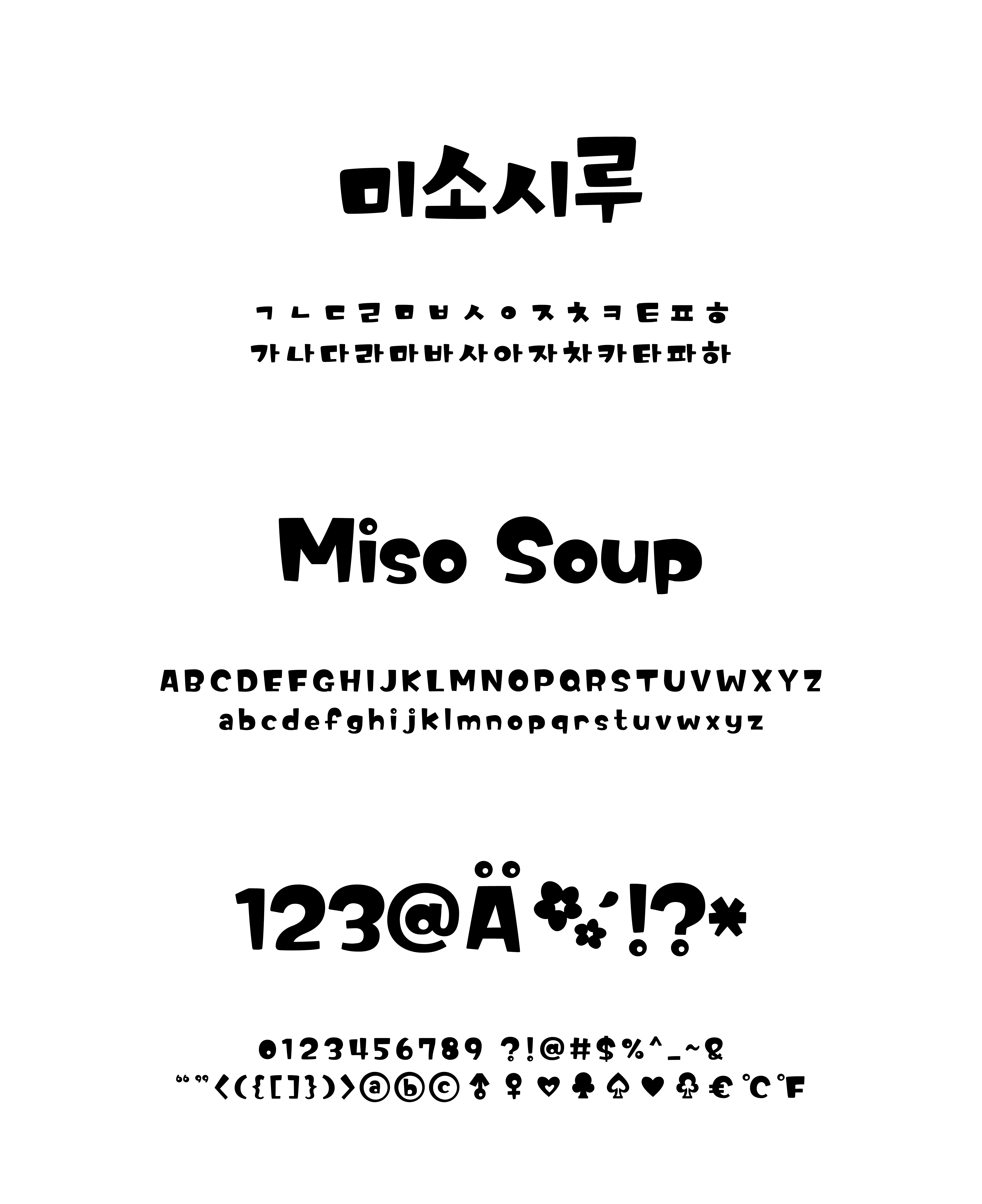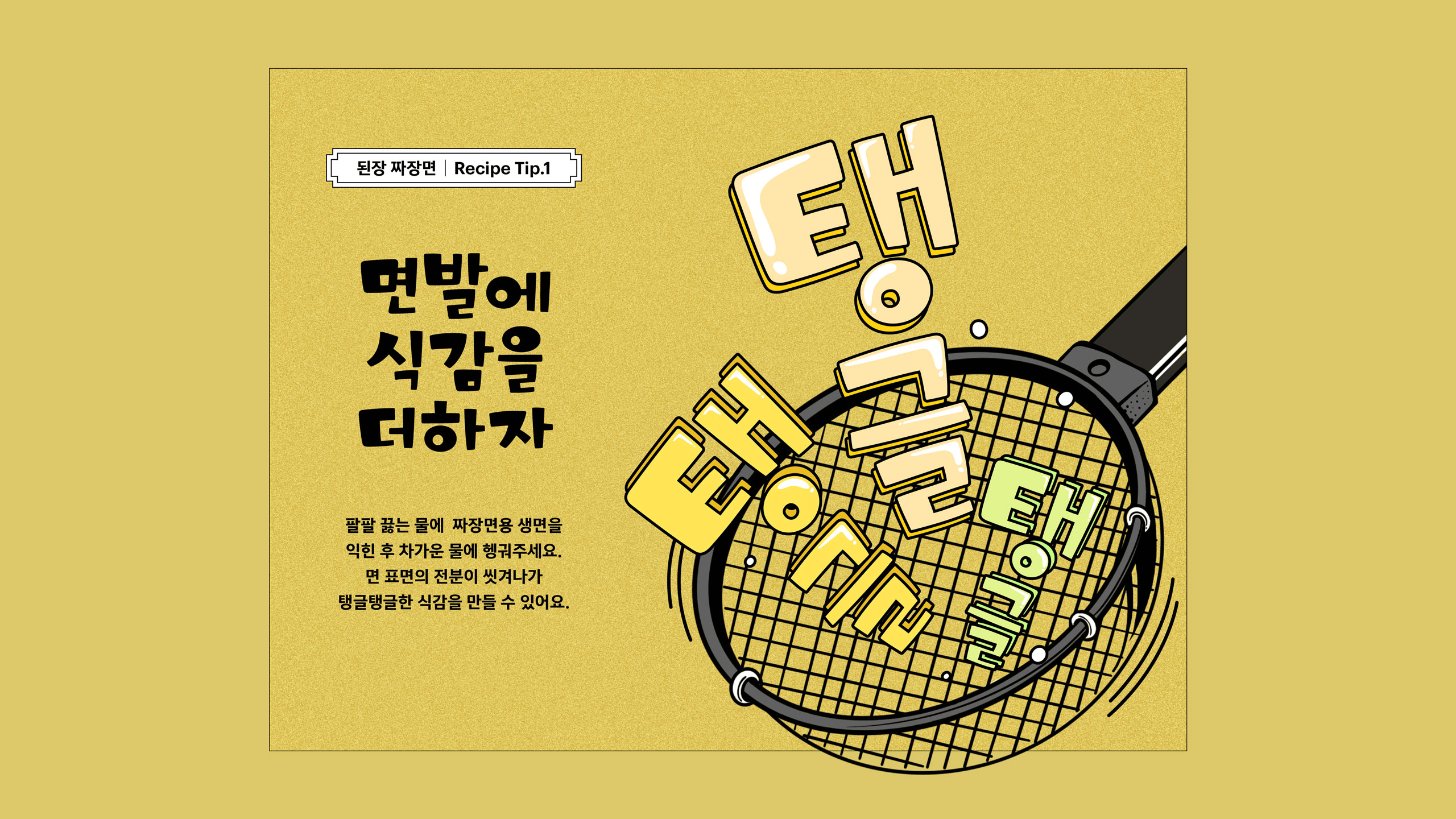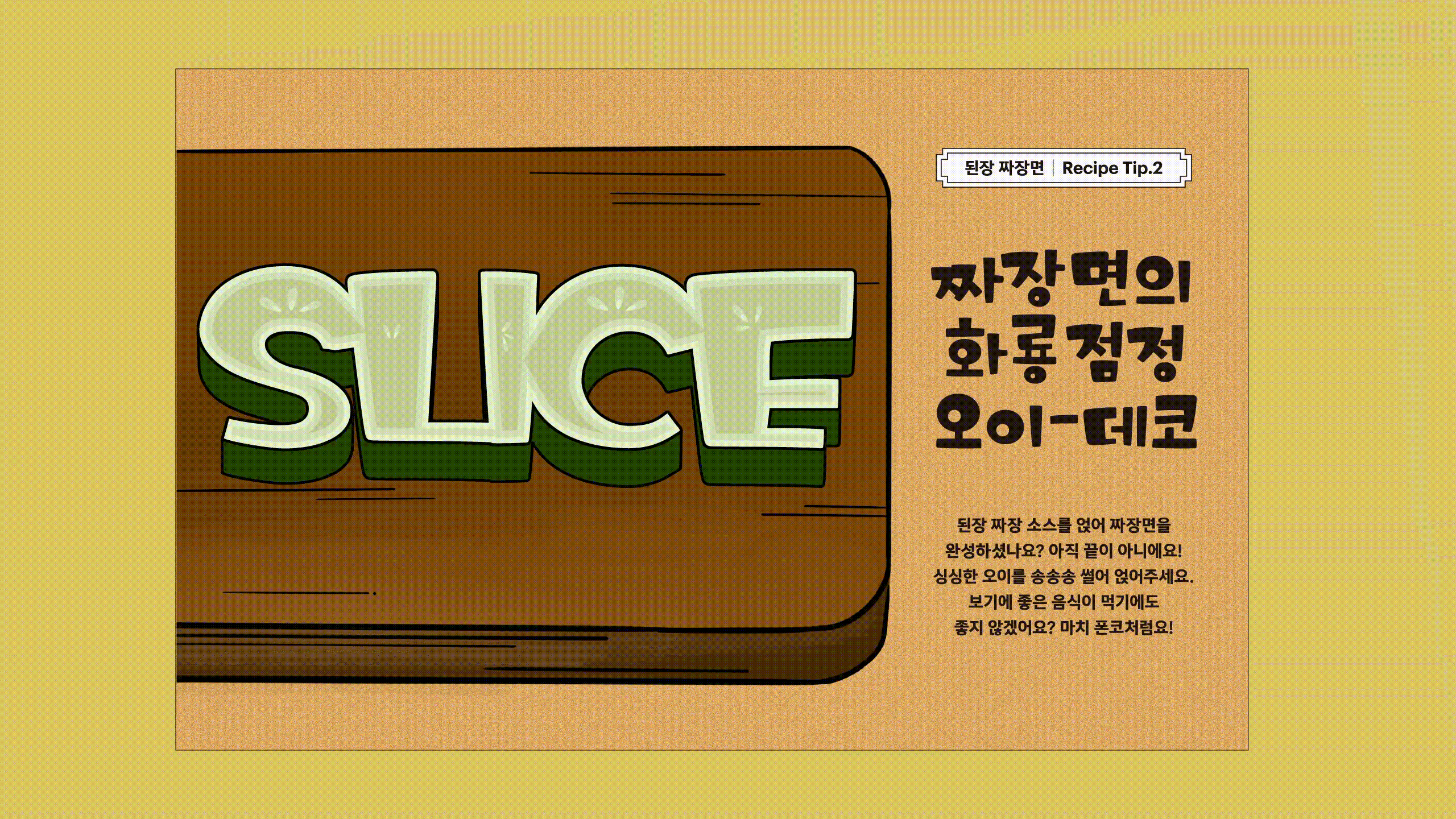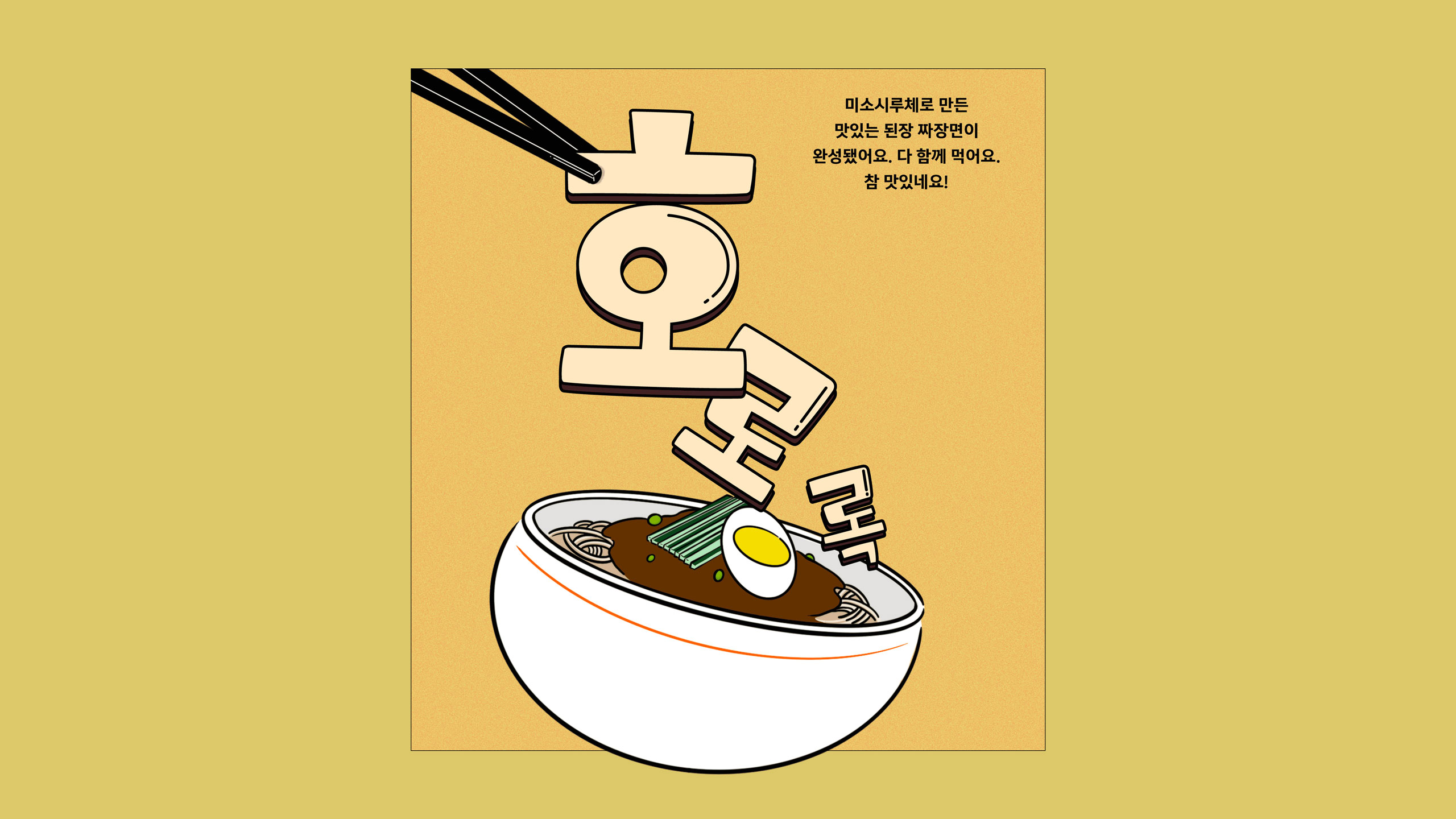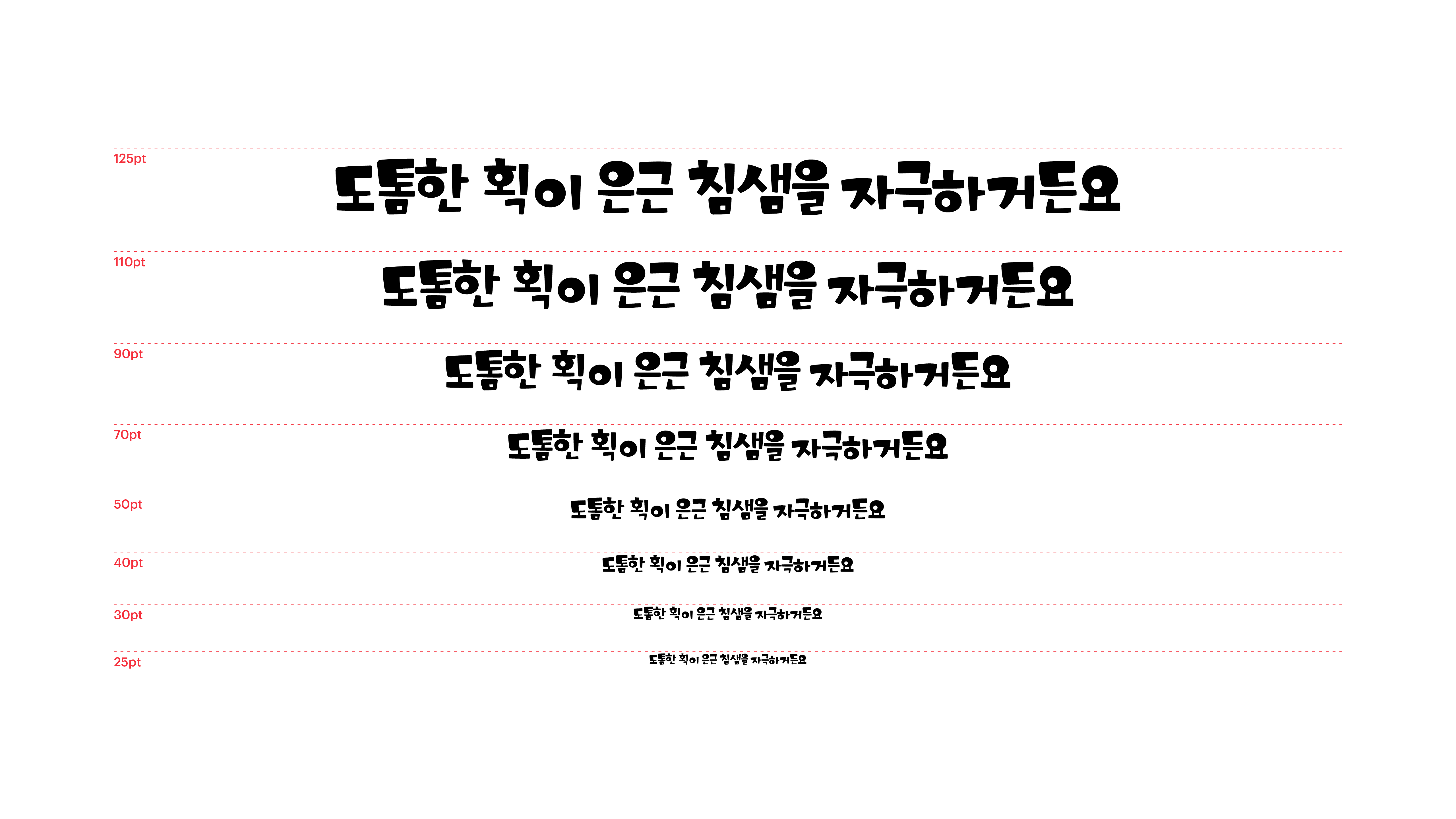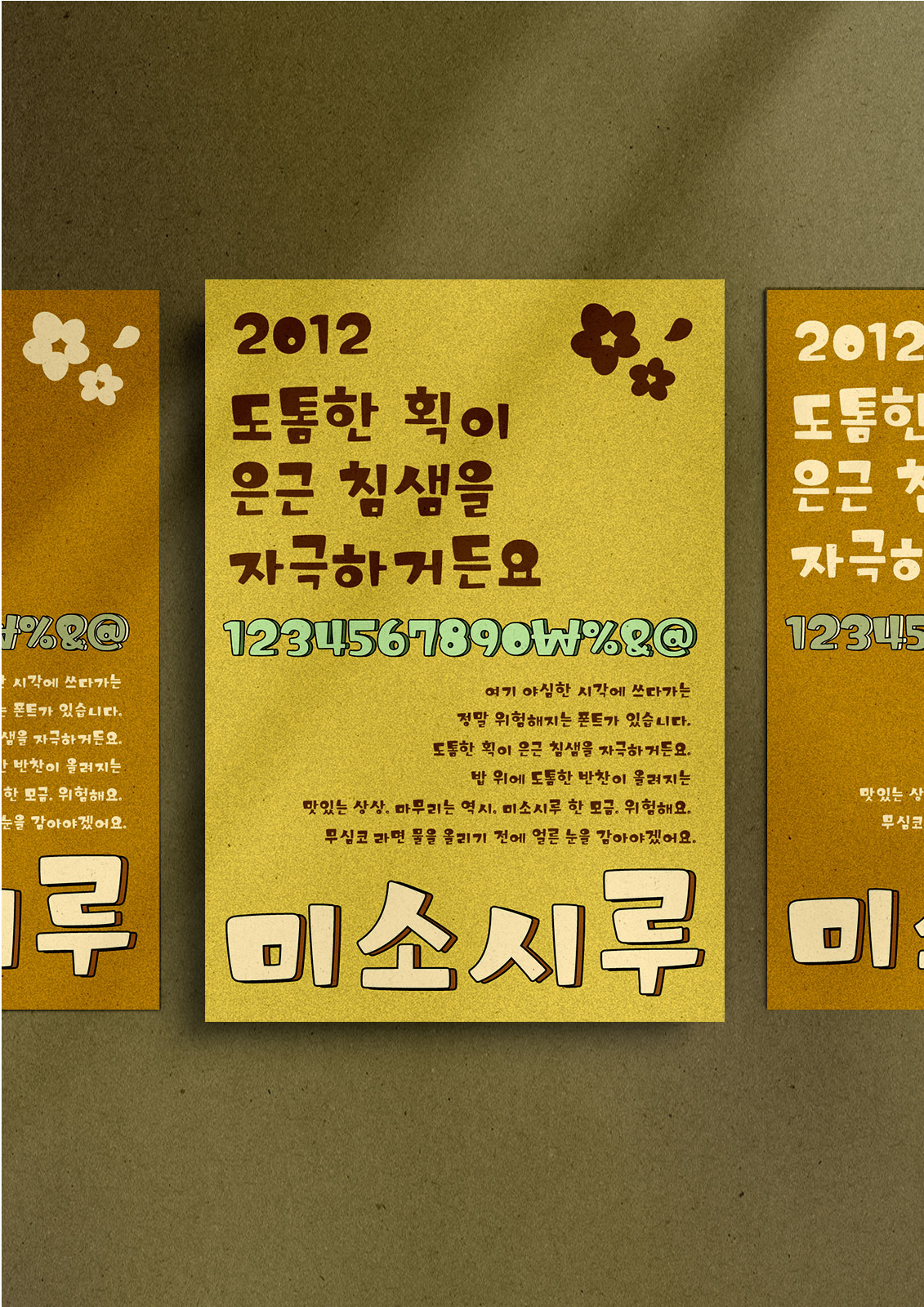
미소시루
Yoon 미소시루
여기 야심한 시각에 쓰다가는 정말 위험해지는 폰트가 있습니다. 도톰한 획이 은근 침샘을 자극하거든요. 밥 위에 도톰한 반찬이 올려지는 맛있는 상상. 마무리는 역시, 미소시루 한 모금. 위험해요. 무심코 라면 물을 올리기 전에 얼른 눈을 감아야겠어요.